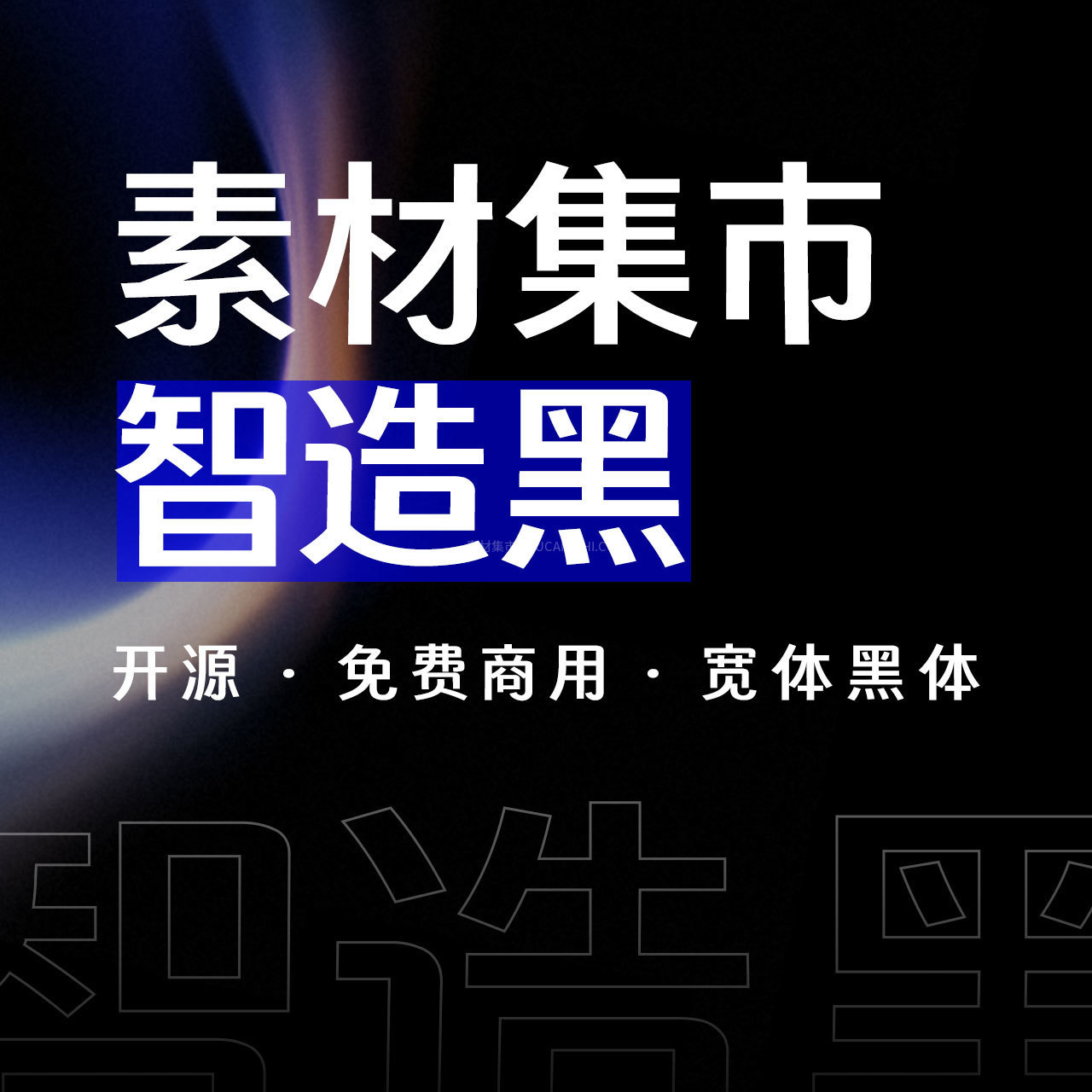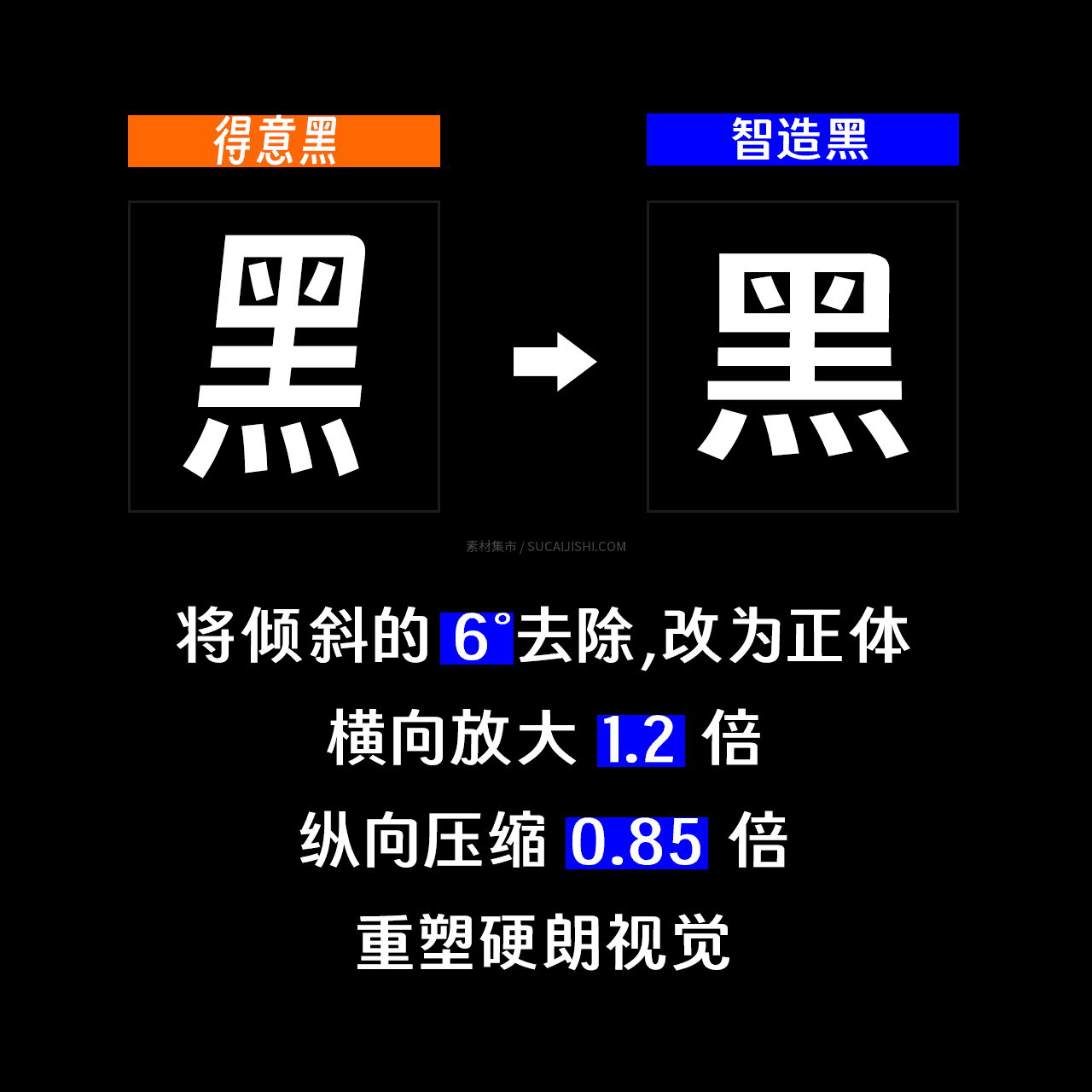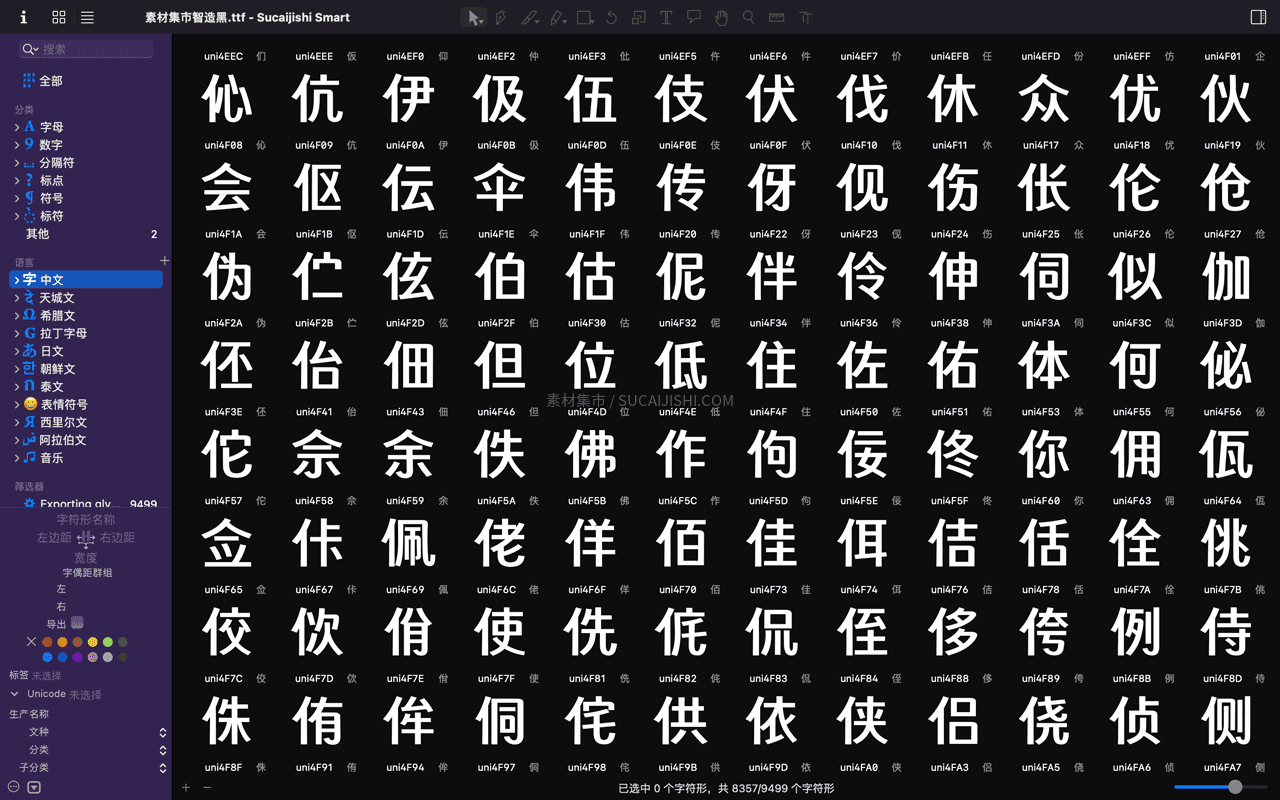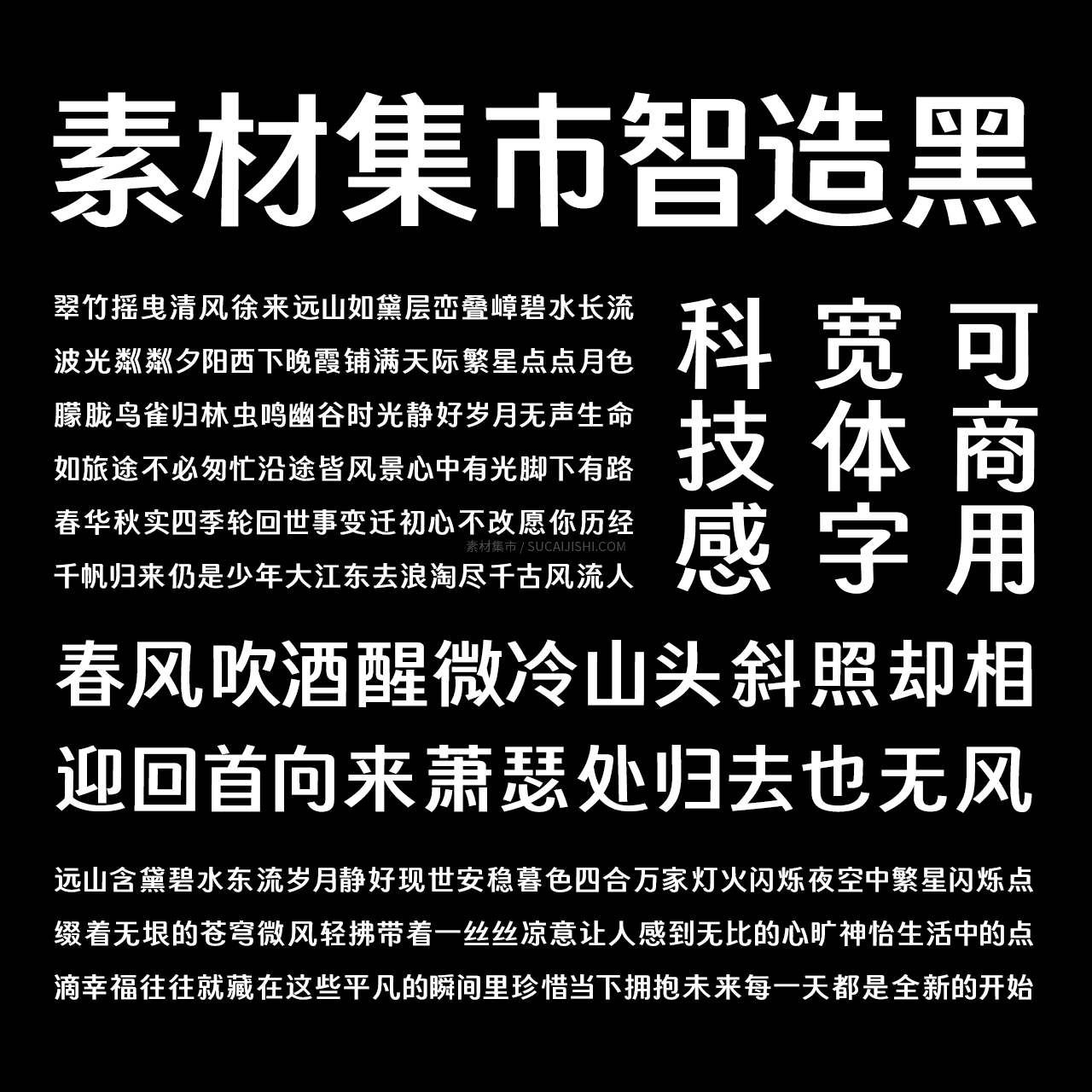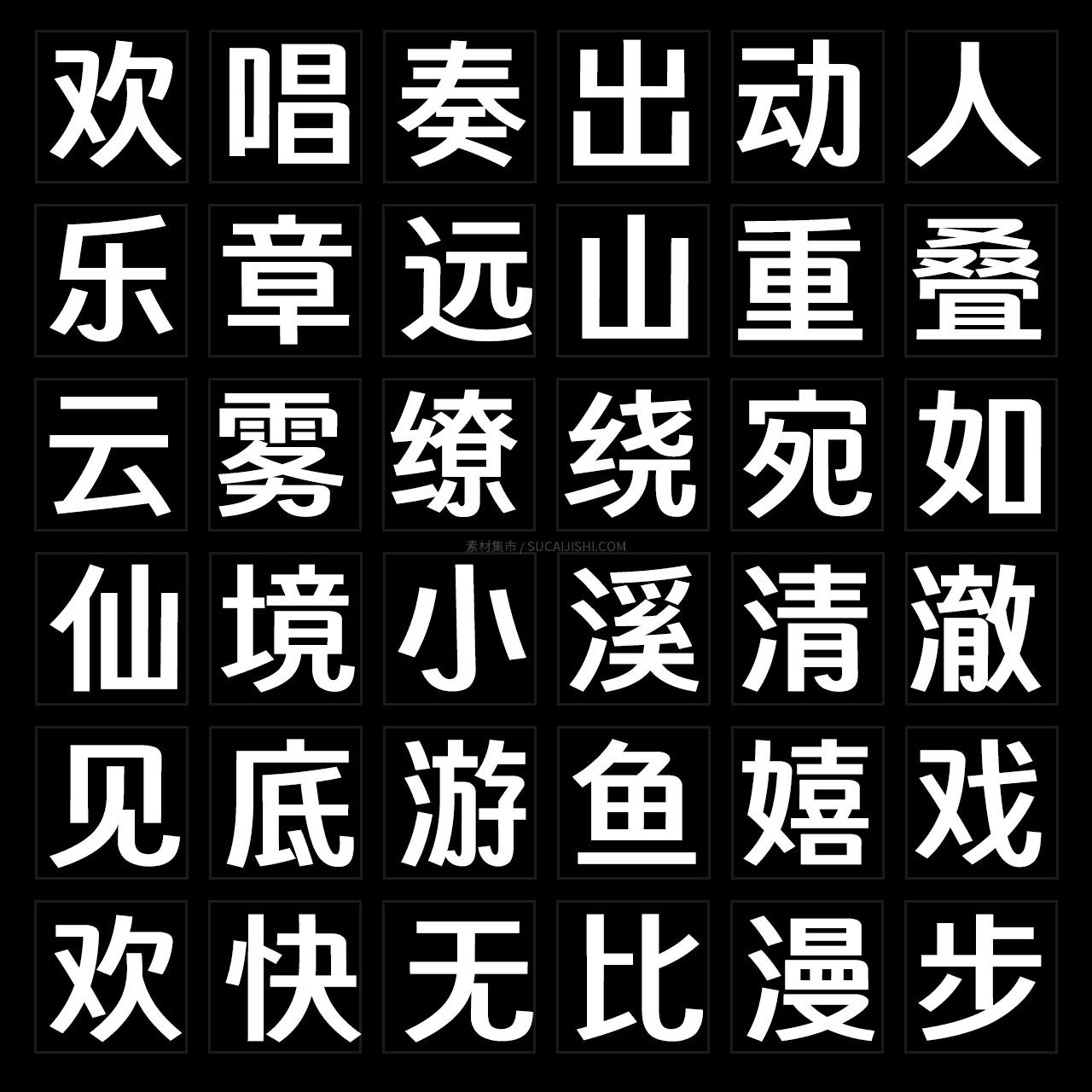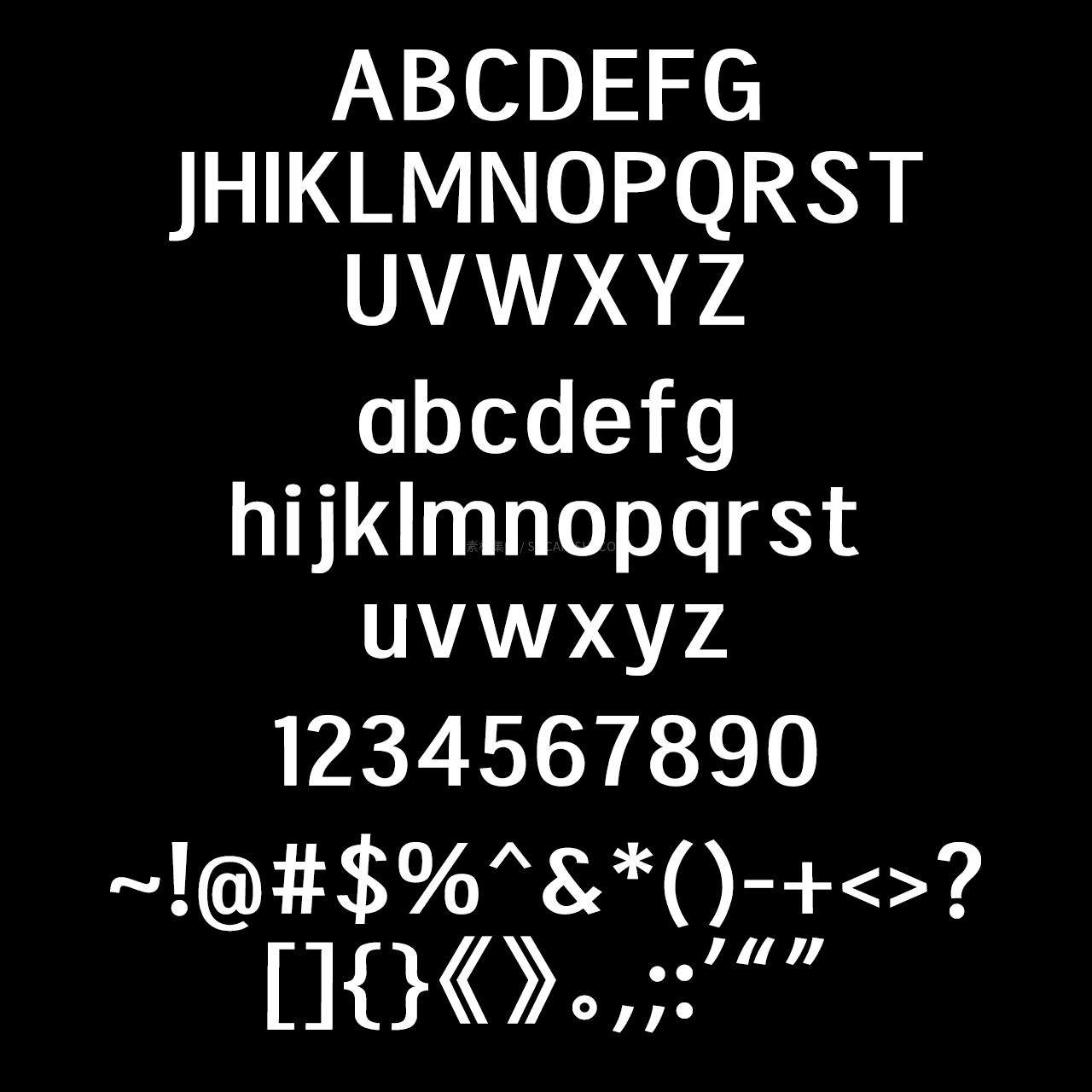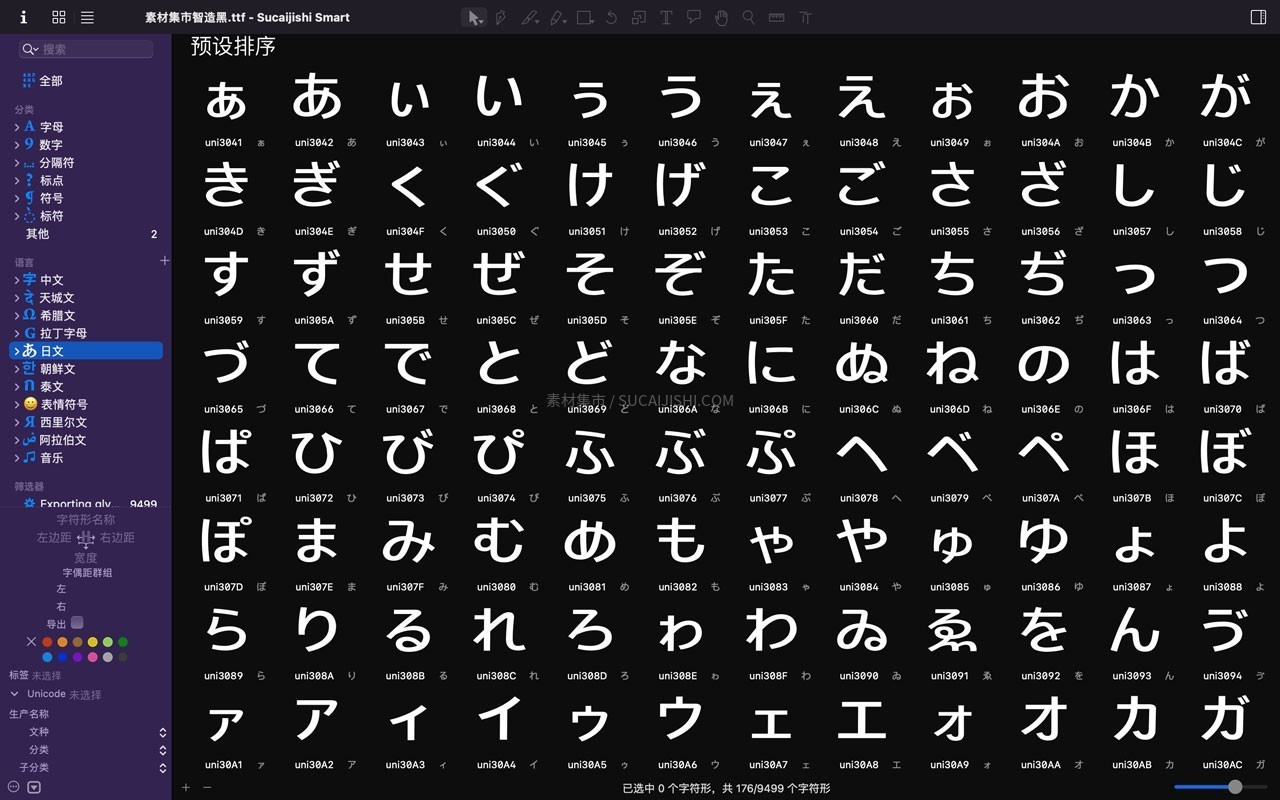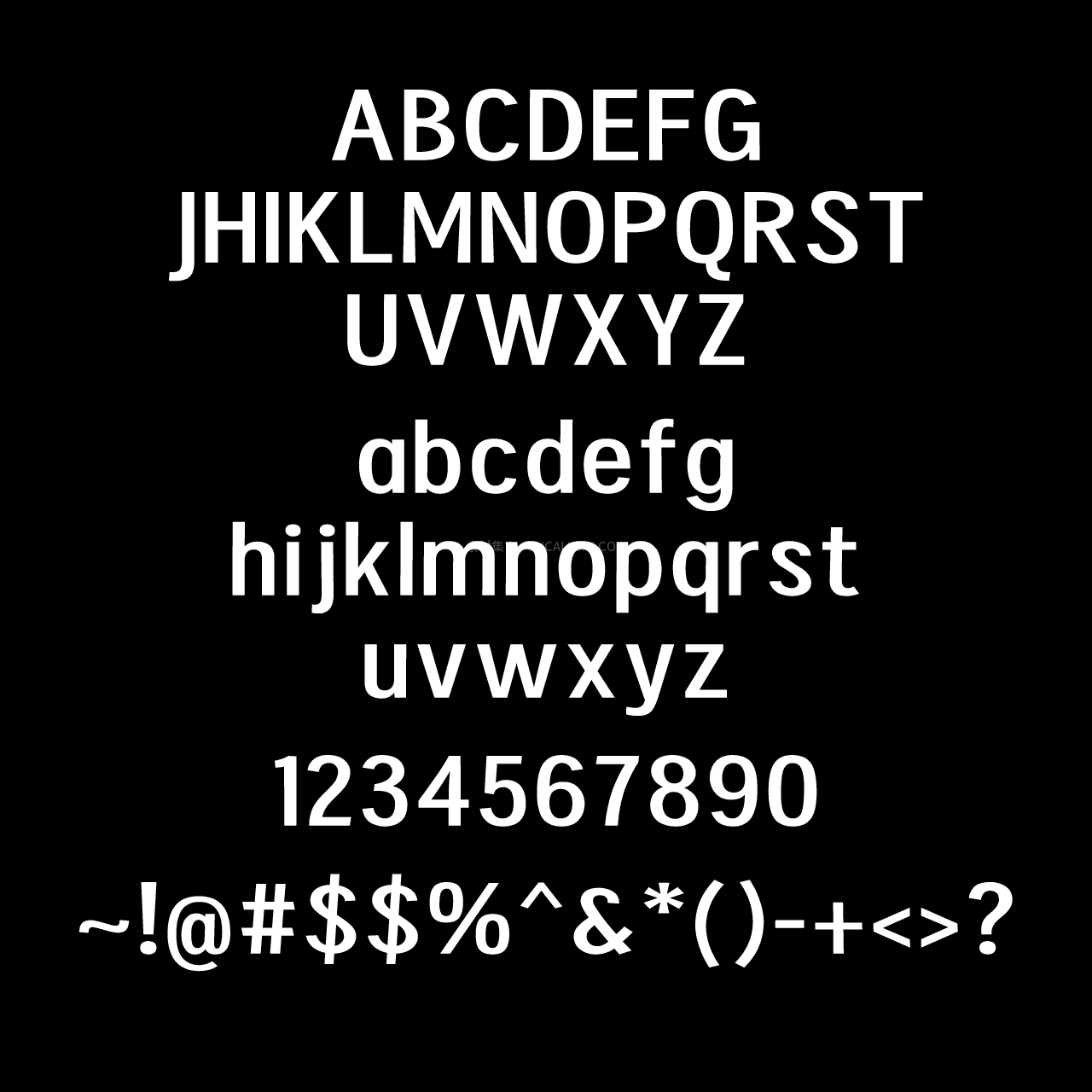
素材集市全新免费商用字体「智造黑」来了!
距离上次发字已经过去整整 6 年,今天我们终于带着全新的设计干货回归了!基于备受欢迎的开源字体「得意黑」二次创作,素材集市智造黑正式亮相。
硬核重塑:褪去跳跃,重铸硬朗宽体
为了让字形完美契合现代工业风与极简设计需求,做了以下调整
• 反向拉直: 抹除原版跳跃的倾斜感,施加 -6 度反向拉直,并向右补偿横向重心,让每个字都能稳稳扎根。
• 宽体比例: 采用“横向拉宽 1.2 倍、纵向压扁 0.85 倍”的重构比例,极大拉升了字面的开阔度与视觉张力。
字库超全:跨语种混排,告别“缺字豆腐块”
作为一款主打实用的干活利器,字库容量直接拉满
• 8335 个中文字符: 完美覆盖 GB/T 2312-1980 与《通用规范汉字表》
• 100+ 种语言支持: 收录 415 个拉丁字母(含变体与本地化字形),轻松搞定英、法、德、西、芬、越等多语种出海项目。
• 174 个日文平假名与片假名
• 80 个基础西里尔字母与 71 个基础希腊字母。
• 除了常规阿拉伯与大小写罗马数字,还内置了 ㈠、②、⑶、⒋ 这种刚需序数字,以及 200 余个特殊标点。